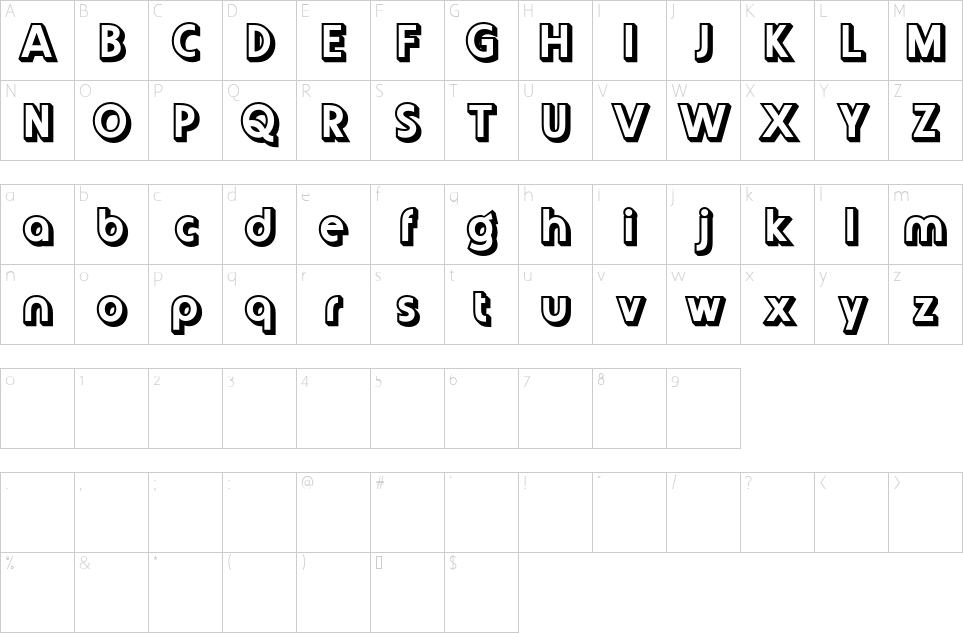
Gerline Font – Download Grátis
A Font Gerline é uma elegante escolha para designers gráficos que buscam um estilo distintivo e versátil. Desenvolvida pela Craft Supply Co., essa font oferece uma gama de opções, desde letras mais leves até as maiores e mais robustas. Suportando tanto sistemas Windows quanto Mac, a Gerline se destaca como uma fonte gratuita com design cuidadosamente elaborado que tem sido baixada pelo número de 107 usuários. Seja para anúncios, artigos de jornal ou qualquer projeto gráfico, a Font Gerline é uma excelente opção para quem busca simplicidade e sofisticação em um único toque. Sua liberdade gratuita permite que designers e aspirantes ao design possam explorar seu potencial sem comprometer o orçamento.